隶书的形成是由篆书衍生而来的,一般字形多为宽扁风格,笔画上横画长竖画短,起笔落笔讲究“蚕头燕尾”“一波三折”。是汉字中常见的一种庄重风格的字体,隶书能够让大家更好地认识书法,传播与发展优秀传统文化。接下来我们一起看看下面字体图片见证古老的书法怎么在设计师的手里焕发出新光彩的吧。
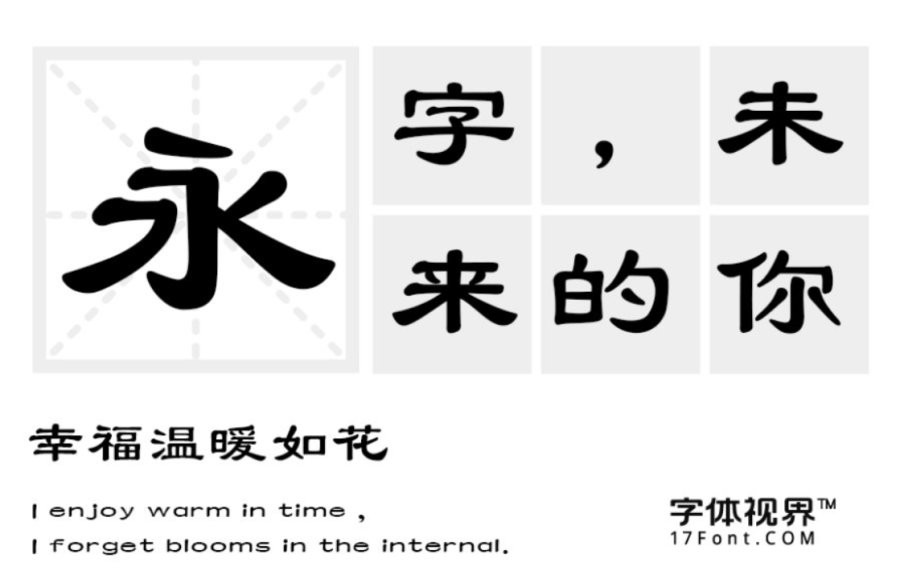
三极隶书简体:这款字体以传统隶书的结构为本并融于隶书笔形特征设计而成,笔画横长竖短,平稳均匀,字形轮廓扁方统一,收放自如。这款字适用于各类传统纸媒,书法作品排版及适用于传统古典类标题、招牌设计。
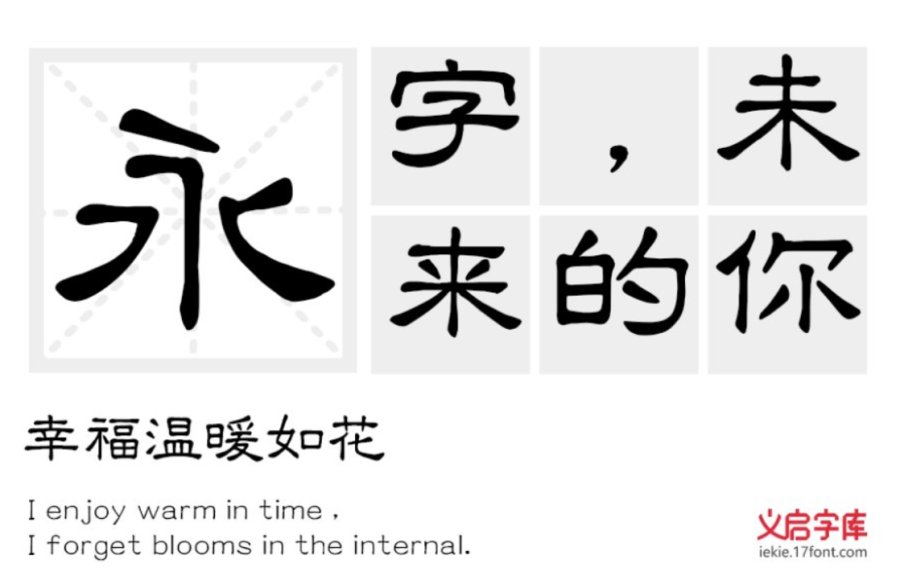
义启隶书体:义启隶书体,笔画上保留深化了波折的元素,由于考虑到整体的可塑性,起收处弱化方笔加强圆笔画,所谓蚕头雁尾修饰弱化些。结构内放外收,整体呈扁方形,重心在一条轴线上,气息通畅一气呵成。适用于标题及正文、logo设计、招牌、印刷等领域。
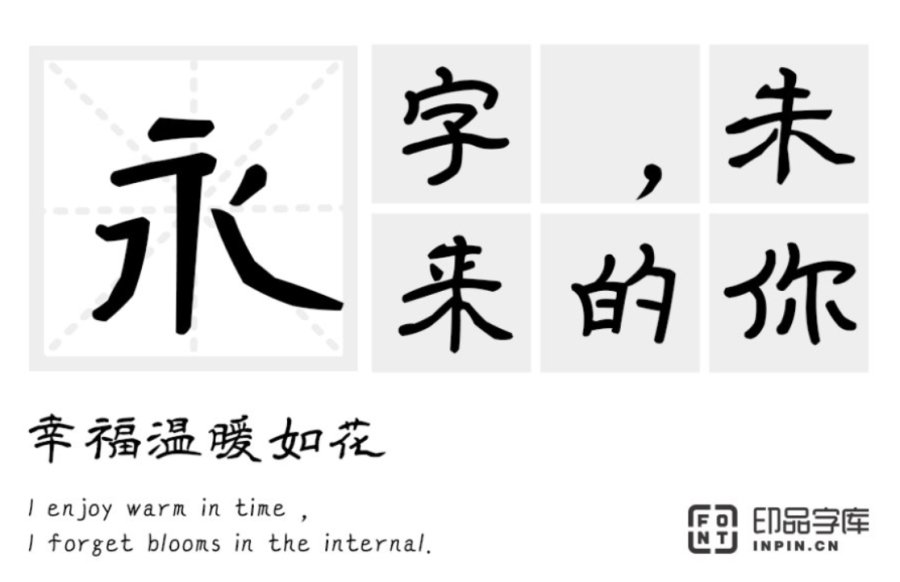
印品征东隶书体:大师经典之作,字形优美,刚柔并济,雅俗共赏。将古风与柔美完美融合,适用于各类阅读体验、标题及正文、logo、招牌、包装设计等领域。